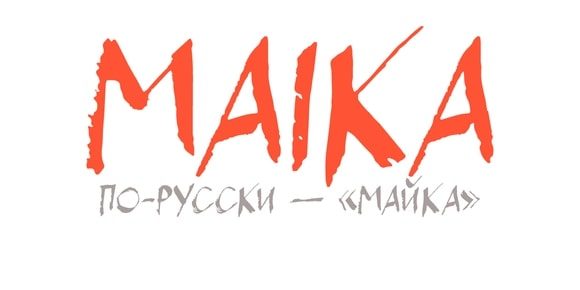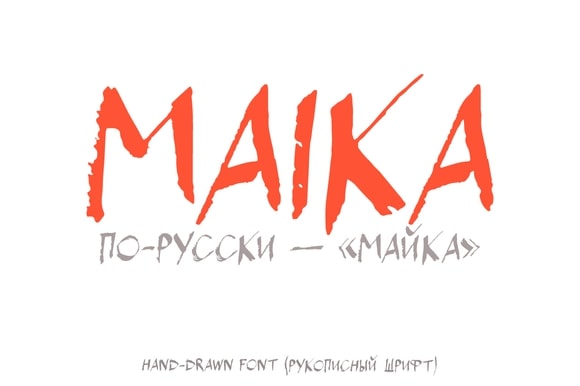
Шрифт Maika
Шрифт Maika — это современный декоративный шрифт в стиле «браш» (кисть), разработанный дизайнером Youhhou . Выпущен в 2016 году на платформе Creative Market. Отличается смелыми, динамичными мазками с эффектом ручной росписи: штрихи имеют переменную толщину и слегка шероховатую текстуру, что придаёт тексту энергичный и художественный вид. Поддерживает кириллицу и латиницу , что делает его подходящим выбором для проектов на русском языке, где требуется выразительный и неформальный акцент. Оцените его характер, и если вы ищете шрифт с «ручным» настроением для ярких задач, вы можете ознакомиться с ним на этой странице.